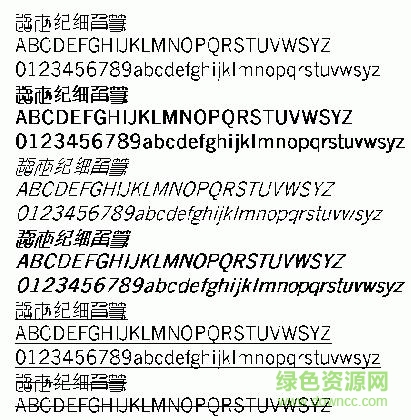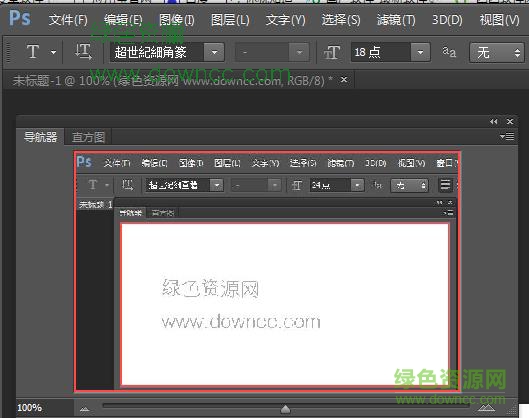
超世紀(jì)細(xì)角篆繁體也是篆書(shū)的一種,字體線條均勻,筆畫(huà)圓潤(rùn)整齊,瘦而有勁。整個(gè)字體雋永非凡,應(yīng)用于橫幅標(biāo)語(yǔ)、美術(shù)設(shè)計(jì)、宣傳海報(bào)、ppt、電視劇制作以及內(nèi)容用字等領(lǐng)域還都是極好的。